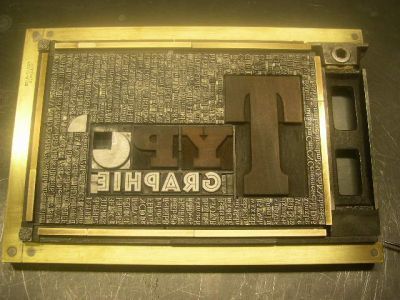
Bullet – Peng!
Zwei Fragen:
• Wie heißt das Bullet-Symbol (•) auf deutsch?
• Findet Ihr es nicht auch in den meisten Fällen zu fett?
Ich mach es fast immer bis zu einem Punkt kleiner als die umgebende Schrift.
Das ist doch ein "Punkt auf Mitte".
Zumindest das untere.
Gehört(e) übrigens nicht zum Standard-Zeichensatz.
Genau so wenig wie Prozent-Zeichen und Schrägstrich uvm.
Kommt immer wieder zu Rückfragen bei Käufern.
Aber € und @ Zeichen - die gibts schon seit geraumer Zeit auch im Bleisatz..
den dünnen kenn ich als zentralpunkt.
in detailtypografie wird er als mittepunkt bzw als fetter mittepunkt bezeichnet.
"Typo-Signal" hört sich gut an. Ich sage ab sofort nur noch "Typo-Signal" anstelle von Bulletpoint. :-)
Ein Kollege von Euch, ein Typograph aus Norddeutschland, hat mal eine Collage als Geschenk für seine Freundin bestellt - ebenfalls eine Typographin.
Bedingung: Die Collage mußte enthalten:
- Das Wort Typographie
- Mindestens ein Berthold Typo-Signal
- Ein bißchen was "überraschendes" sollte mit drin sein.
Entstanden ist die Collage "O kaputt":
Entstanden ist die Collage "O kaputt"
Coole Sache! Da ist’s fast schade, dass mein Schätzchen bei der Bank arbeitet.